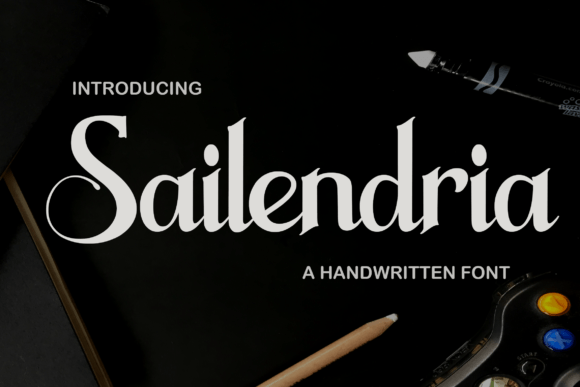
Sailendria
Znalezienie odpowiednich elementów projektu może być wyzwaniem, ale Sailendria oferuje wyjątkową kolekcję, która natychmiast ulepszy Twoją pracę.
Niezależnie od tego, czy tworzysz produkty POD (druk na żądanie), zaproszenia ślubne czy grafiki do mediów społecznościowych, Sailendria będzie idealnym wyborem.